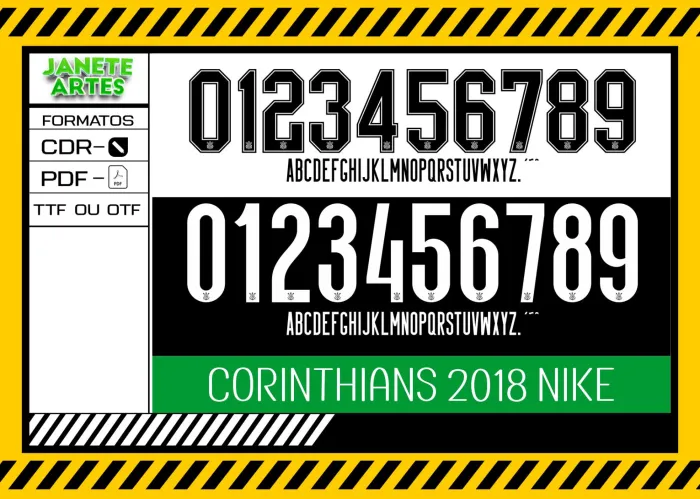
Fonte de Time Tipografia Corinthians 2018
Uma História de Paixão pelo Corinthians
Imagine você reunido com a galera para assistir a um clássico do Corinthians, todos vestindo camisetas personalizadas que destacam a identidade do time! Foi assim que a paixão pelo futebol ganhou uma nova forma na vida do Lucas, um torcedor fervoroso que queria algo único. Ao baixar a Fonte de Time Tipografia Corinthians 2018, ele conseguiu criar camisetas incríveis para a torcida, unindo estilo e tradição. O resultado? Um time unido, vibração contagiante e aquele orgulho de vestir algo que representa de verdade seu amor pelo Corinthians.
- Tipografia exclusiva do Corinthians 2018 para personalização de camisetas, camisas e blusas.
- Perfeito para criar estampas grandes nas costas e detalhes no peito.
- Ideal para uso profissional ou amador na impressão têxtil.
Dicas e Ideias para Personalizar
- Combine a tipografia com o logo do Corinthians para um visual marcante.
- Use camisetas na cor preta para destacar a impressão com mais contraste.
- Perfeito para eventos, turmas de amigos, times de futebol amador e presentes especiais.
- Cuidados na hora da impressão: escolha tecidos de qualidade para melhorar o acabamento.
- O que significa 'Fonte de Time Tipografia Corinthians 2018'? É o estilo de letras usado pelo Corinthians na temporada de 2018, ideal para personalizar produtos com identidade do time.
Com o Arte Fonte Corinthians 2018 Tipografia Time, você tem um produto que traz paixão, estilo e identidade para suas criações. Seja para uso pessoal ou profissional, ele transforma camisetas e blusas em peças exclusivas que encantam torcedores e amigos. Aproveite para inovar, criar e vibrar junto com seu time com essa fonte incrível!